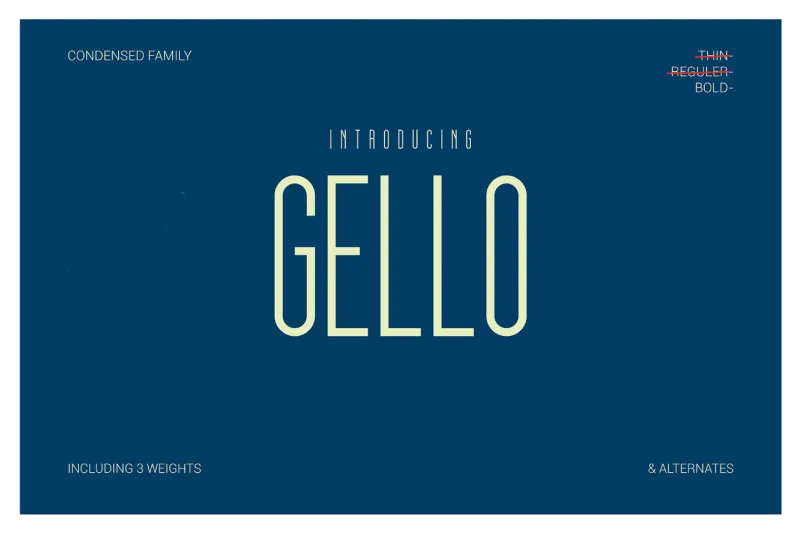
Gello Display Font – Download Grátis
Descubra a beleza minimalista do Gello Display Font. Inspirado na simplicidade, essa fonte oferece uma elegância sofisticada através de sua forma não-serif caracterizada por seu slimness e altura elevada. É perfeitamente adaptada para criações que buscam um estilo moderno e limpo. Como designer ari o projetou especialmente para san serif type, trazendo consigo um ar de elegância refinada. O Gello Display Font é perfeito para aplicar em seu próximo projeto gráfico, seja ele uma página web ou um layout impresso. Com sua simplicidade impressionante e beleza elegante, ele complementará o seu design sem questionar a essência da sua ideia. Descubra como essa fonte pode transformar o visual de seus projetos.